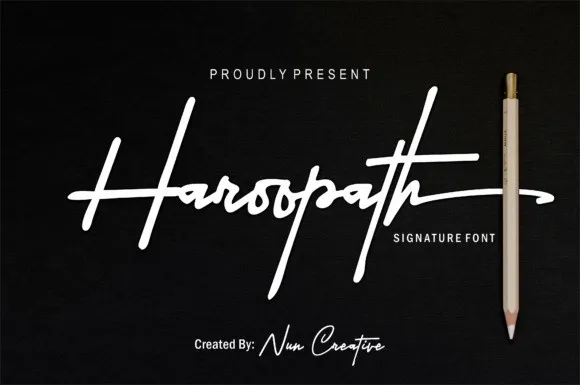
Haroopath Signature Font – Download Grátis
Olá! Se você está procurando uma fonte que ofereça tanto charme quanto funcionalidade, a Haroopath Signature Font é uma excelente opção. Esta tipografia script é perfeitamente adaptada para projetos de identidade visual como marcas e logotipos, designs para casamentos, postagens nas redes sociais, anúncios, embalagens de produtos, designs de produto, rótulos, fotografias, marcações, convites e material de papelaria. Com sua elegância moderna e estilo handwritten, ela é um toque suave que tornará qualquer projeto mais atraente e agradável aos olhos. Seu aspecto natural também oferece uma sensação de autenticidade perfeita para diversos projetos, garantindo que seu design seja único e imprimível. Em um mundo repleto de estilos, a Haroopath Signature Font se destaca pelo seu encanto inato, tornando-a uma escolha ótima para quem busca harmonia e elegância em suas produções visuais.